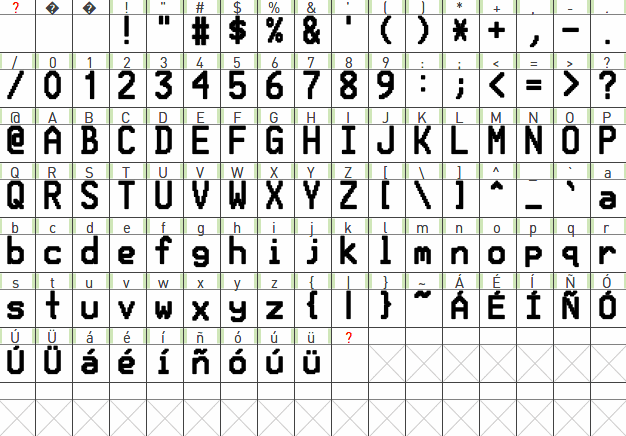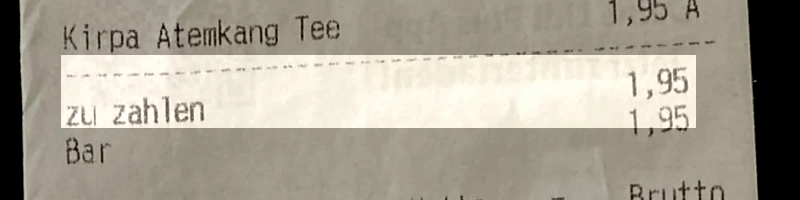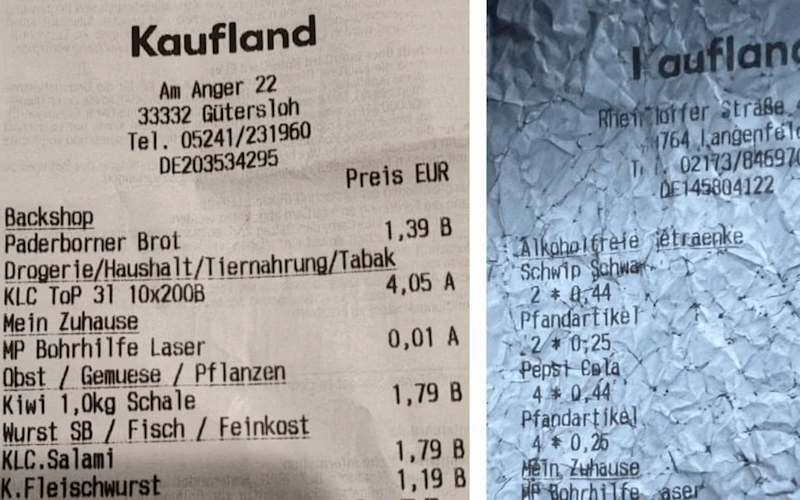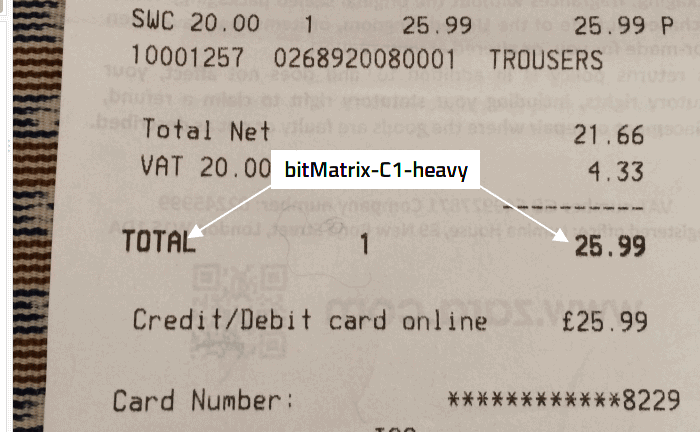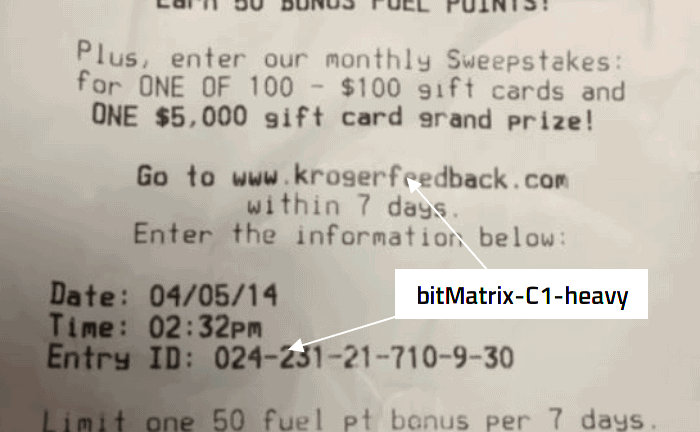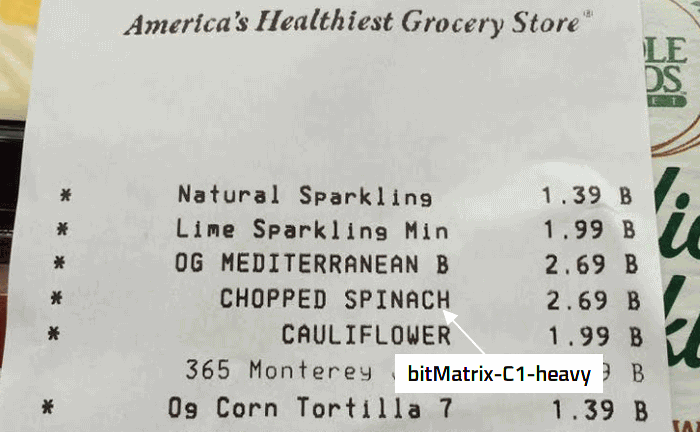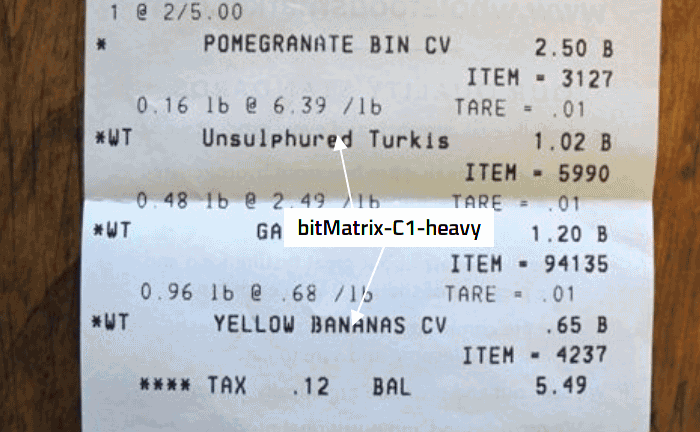
Eine schwere, fette Schriftart auf vielen Arten von Rechnungen
verwendet, um wichtige Daten auf Belegen zu drucken
Eine schwere, fette Schriftart auf vielen Arten von Quittungen
Alle Zeichen der Schriftart⤴
gedrucktes Sample von der Schriftart⤴